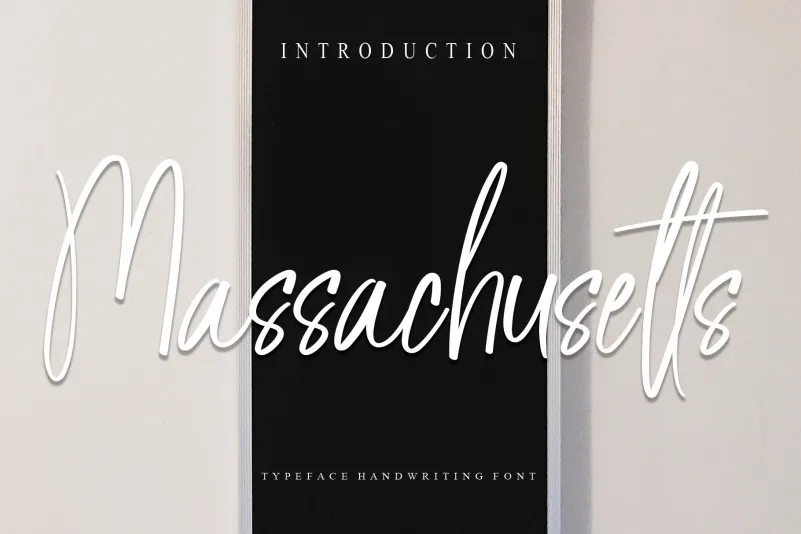
Aqui está uma breve descrição para a página de download da font ‘Massachusetts Script Font’, focada na categoria de letras manuscritas criadas pelo designer creativeletter: Na sua busca por um estilo elegante e sofisticado, você encontrará no Massachusetts Script Font uma opção perfeita. Criada para dar vida a qualquer projeto gráfico, esta linda fonte segue as linhas do ‘Handwritten Fonts’ categorias oferecendo uma experiência de escrita única. Com traços suaves e detalhes meticulosos, o Massachusetts Script traz um toque autêntico e personalizado às suas criações. Seja para revistas, perfis profissionais ou artigos de design gráfico, esta fonte é a escolha ideal para dar à sua produção uma aparência única. Compostas em letras elegantes e fluidas que parecem ter sido escritas por um artista plástico versátil, as linhas da Massachusetts Script fornecem ao designer uma maneira de expressar personalidade e estilo nos textos. Seja para títulos, subtítulos ou o próprio corpo do texto, esta fonte é perfeita para dar vida à sua marca. Cada caractere dessa elegante fonte foi cuidadosamente criado para oferecer um grau exato de leitura confortável e aparência impecável. É uma font que permite a criatividade e a personalização, oferecendo aos designers o poder de moldar seus materiais em qualquer formato desejado. A Massachusetts Script é mais do que apenas uma fonte; ela é um complemento perfeito para quem busca criar projetos com um toque especial. Este é um recurso gráfico que certamente vai revolucionar sua rotina criativa e lhe dará a oportunidade de fazer maravilhas no mundo da design visual.